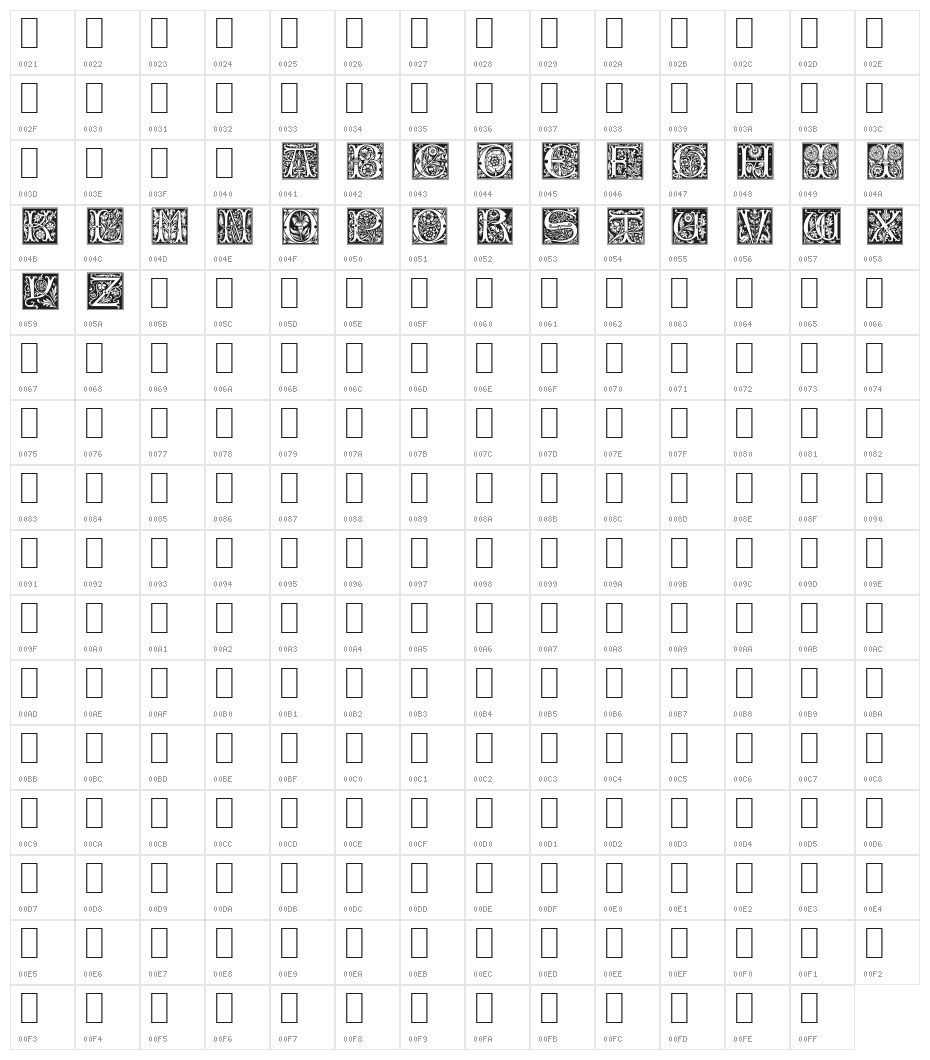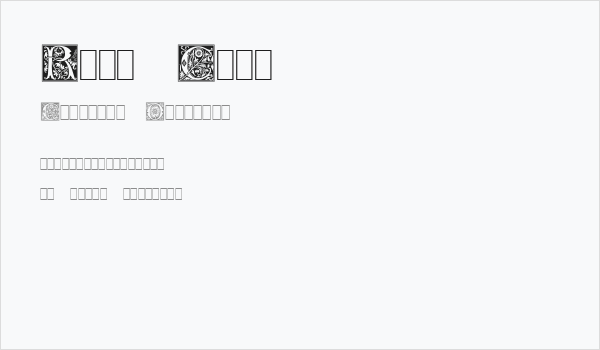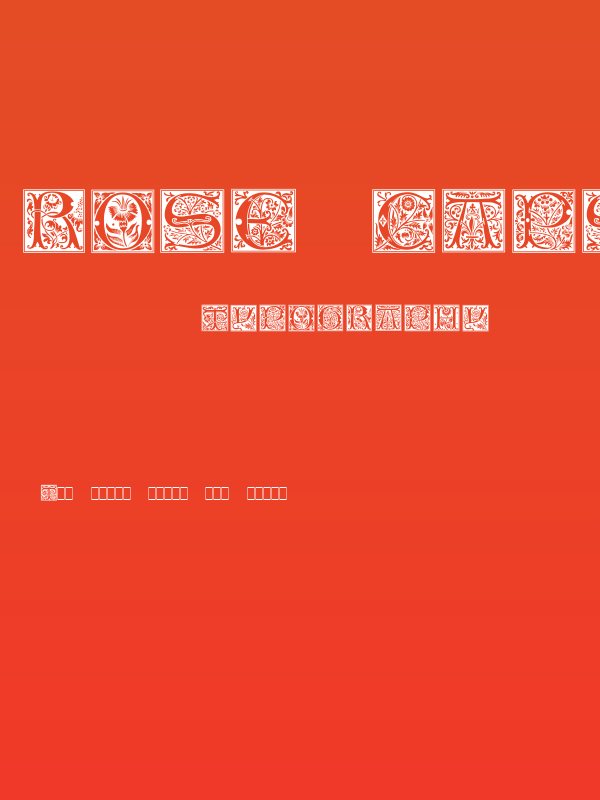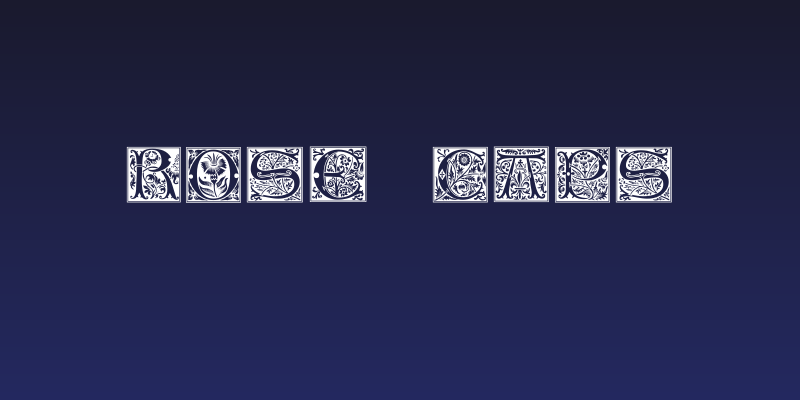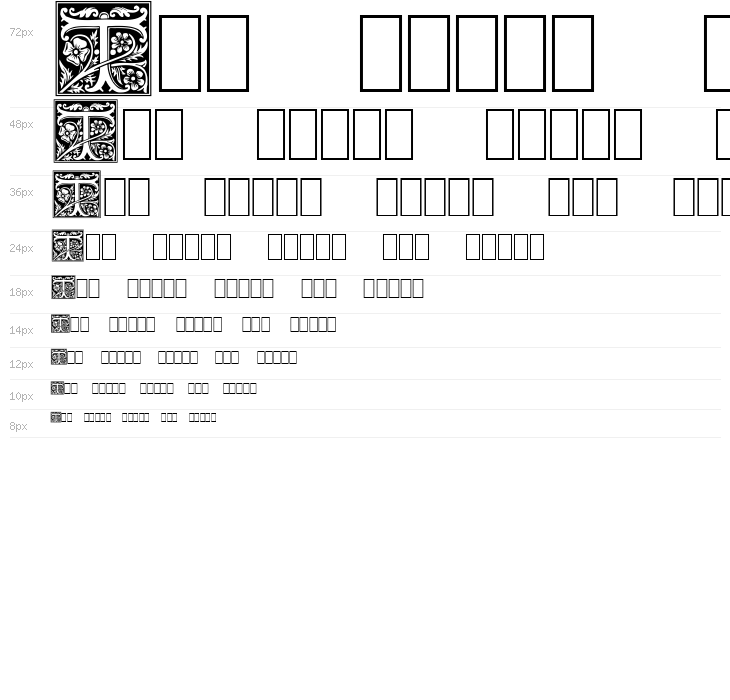
Rose Caps Font
✎ Gothic
| Categorie | Gothic |
| Caso d'uso | Logos, Headlines, Decorative purposes |
| Progetti proposti | Ideal for wedding invitations, vintage-themed posters, decorative book covers, or any project requiring a touch of classical elegance. |